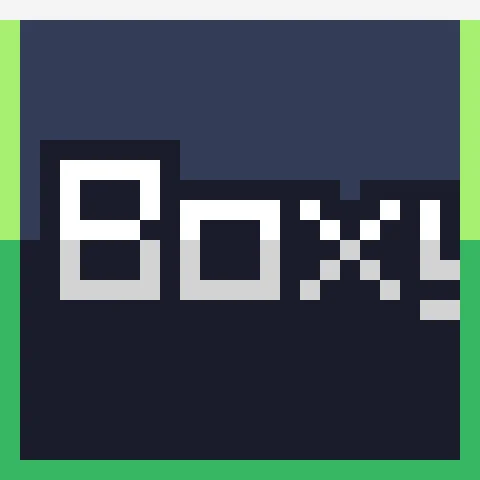
Slyme's Boxy Font
Шрифт с острыми углами и ретро-стилем для Minecraft. Идеальная замена Mojangles, если хочется чёткости и ностальгического вайба.
Если стандартный шрифт в Minecraft - Mojangles - кажется тебе слишком круглым и размытым, а хочется чего-то более чёткого и угловатого, то Slyme's Boxy Font - твой выбор.
Что это и зачем нужно
Boxy Font - это простой ресурспак, который меняет шрифт в игре на более острый и угловатый. Все буквы становятся менее скруглёнными, приобретают ретро-вид, напоминающий старые пиксельные игры. Шрифт смотрится чище и резче, особенно на маленьких экранах или при высоком разрешении.
Если тебе надоели плавные линии стандартного шрифта и хочется добавить в Майнкрафт больше пиксельного хардкора - Boxy Font справляется с этим на ура.
Как работает
Автор заявляет, что шрифт остряет углы у всех букв. Правда, на момент написания - не все знаки из nonlatin_european.png были переделаны. То есть с кириллицей могут быть нюансы - часть символов останется стандартными, часть станет острее. В целом, для английского языка всё ок, а вот на русском возможны мелкие несоответствия. Но большинство букв должно быть в порядке.
Кому подойдёт
- Тем, кто любит пиксельную графику и ретро-стиль.
- Кто хочет сделать интерфейс более читаемым и резким.
- Кому Mojangles кажется слишком мягким.